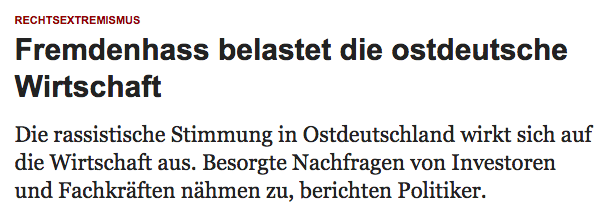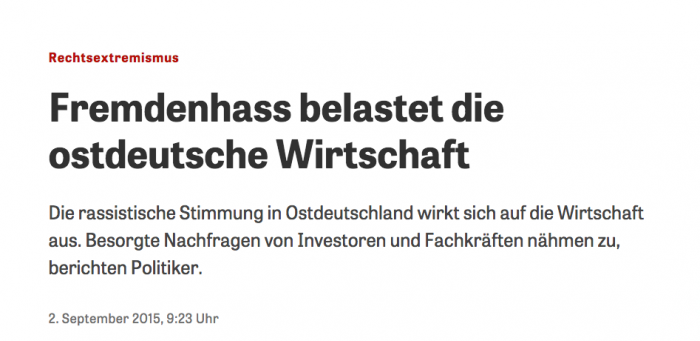
Serifenlose nach Relaunch von "Zeit-Online"
Ist für euch bestimmt nicht schwer zu bestimmen, aber ich komme leider einfach nicht drauf.
Welche Serifenlose wird für Headlines bzw. Unterüberschriften auf der relaunchten Zeit-Online-Website verwendet (siehe Anhang)?
Auf der Website wird die Arial verwendet, in deinem Screenshot aber nicht. Woher stammt der denn?
in Chrome:
Oweia, sollte sich das um eine Browser-Einstellung handeln? Der Screenshot stammt von heute, Google Chrome für Mac. Wenn ich die Seite über Firefox aufrufe, habe ich tatsächlich auch die Arial. Kam ich bisher nur nicht drauf.
Dann hast du was an deinem Chrome verbastelt :-)
... Chrome verbastelt - so leicht geht ein Web-Relaunch ;-)
Würde mich aber trotzdem interessieren, wie die verbastelte Schrift heißt.
Danke schonmal! Kommt schon gut hin, die Tablet Gothic.
Ich fühlte mich auf den ersten Blick an die Adelle Sans erinnert, aber die war es nicht. Ist aber kein Wunder, an beiden hat Veronika Burian gearbeitet ...